Шрифт для выжигания по дереву: как подготовить буквы к переносу
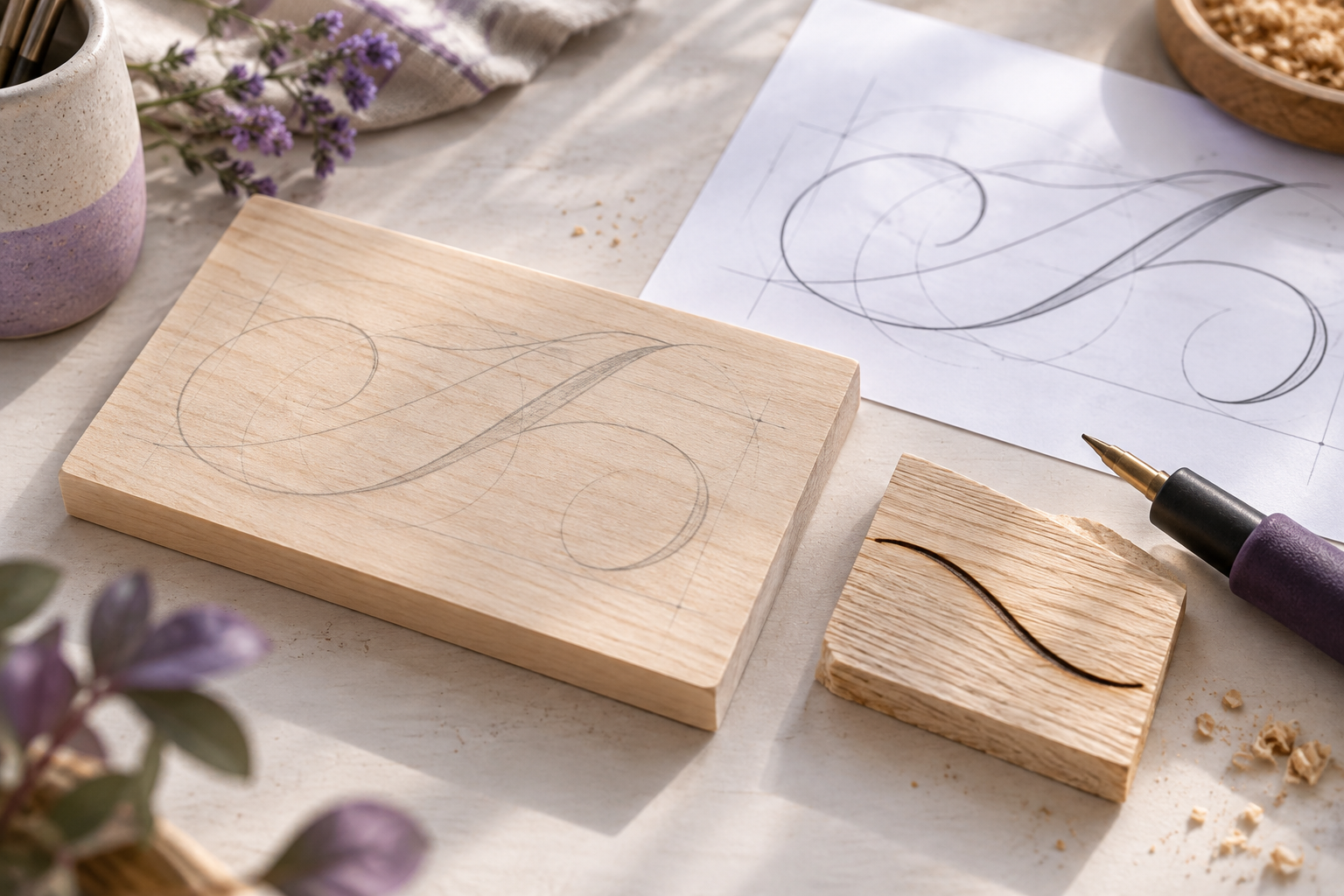
Надпись пирографом на дереве начинается не с выбора красивого шрифта, а с проверки того, какие его детали выдержат перенос и движение горячего пера. На древесине штрих может выглядеть иначе из-за направления волокон и неодинакового потемнения, поэтому готовый макет стоит упростить и испытать на обрезке того же материала.
Почему экранный макет не переносится на дерево один к одному
На экране буква выглядит как контур заданной толщины и ровного цвета. При выжигании её рисует не пиксель, а наконечник инструмента, который движется по поверхности и оставляет след с собственной шириной. На практике линия получается не абсолютно одинаковой на всём протяжении: на результат влияют скорость движения руки, контакт с поверхностью, древесный рисунок и выбранный наконечник. Поэтому тонкий штрих может стать слабым или прерывистым, а тесный просвет между элементами — закрыться.
Важно заранее решить, какую роль играет надпись. Короткое имя на небольшой подвеске можно сделать выразительным и крупным; фраза на табличке должна читаться с расстояния; длинная цитата требует прежде всего ровного ритма и достаточного межстрочного пространства. Один и тот же декоративный шрифт не одинаково подходит всем этим задачам. Сначала определяют формат изделия и расстояние чтения, затем выбирают характер букв.
На экране удобно масштабировать макет без потери качества, но физическая заготовка задаёт предел. Если надпись должна уместиться в узкой зоне между краем, креплением и естественным сучком, уменьшение целого макета одновременно сокращает внутренние просветы и расстояния между словами. Если свободного поля нет, лучше сократить текст или перестроить композицию, чем механически уменьшать кегль.
Как выбрать шрифт для пирографии
Для первой пробы выбирайте гарнитуру по силуэту слова, а не по названию стиля. Напишите реальную фразу в предполагаемом размере и посмотрите на неё целиком. У букв «о», «а», «е», «в» и «р» проверьте внутренние пространства; у «ш», «щ», «м» и «ж» — участки, где несколько штрихов сходятся близко. Если контуры уже на экране сливаются, выжигание не исправит проблему. Хороший кандидат читается в масштабе изделия без увеличения.
Рукописный шрифт может передать ручной характер вещи, но его петли и связки нужно оценивать отдельно. Соседние буквы не должны превращаться в сплошной тёмный участок после нанесения линии. Геометрический или нейтральный гротеск обычно проще для первой технической проверки: у него легче заметить тесные интервалы и сравнить ширину штрихов. Это не запрет на декоративные формы, а способ сначала проверить основу, а затем добавлять характер.
Не имитируйте толщину букв двойным проходом по контуру, если задача — получить обычную линейную надпись. Контурная буква требует замкнутой формы и отдельной проверки того, как будут выглядеть её внутренние и внешние линии. Для имитации плотного штриха иногда нужна обводка или заполненная форма, но на дереве такой участок может потребовать больше времени и дать неравномерный тон. Решение принимают на пробе, а не по экранному превью.
Откройте мелкие детали до переноса
В макете полезно увеличить те части, которые при уменьшении становятся особенно уязвимыми: внутренние просветы, короткие перекладины, острые соединения и тонкие окончания. Уменьшите текст до реального размера и распечатайте на обычной бумаге либо выведите рядом с контуром заготовки. Просмотрите его не только вблизи, но и с расстояния, с которого человек будет читать готовое изделие. Если слово узнаётся лишь при разглядывании листа, на готовом предмете оно тоже потребует лишнего усилия.
Вместо точного миниатюрного набора часто лучше слегка изменить рисунок: выбрать менее контрастное начертание, увеличить расстояния между буквами, убрать чрезмерно тонкие элементы или заменить сложную связку более ясной. Не растягивайте весь текст непропорционально только ради заполнения поля: буквы могут выглядеть деформированными. Настраивайте интервал и масштаб в пределах, при которых форма сохраняет привычные пропорции.
Отдельно проверьте сочетания русских букв, которые могут напоминать друг друга при малом размере, и знаки, важные для смысла: тире, точку, запятую, двоеточие. Если надпись содержит дату или инициалы, проверьте цифры и их порядок. Пирография превращает крошечную типографическую ошибку в постоянную отметку, поэтому тестовый набор должен повторять именно окончательный текст, а не условное слово из одинаковых букв.
Учитывайте волокна, сучки и направление композиции
Перед версткой разложите заготовку в том положении, в котором её будут рассматривать. Отметьте верх, низ, лицевую сторону, крепёж и участки, которые будут скрыты или закрыты рукой. Затем посмотрите на направление волокон и заметные природные особенности. Они не являются дефектом, который нужно маскировать любой ценой: задача в том, чтобы надпись оставалась различимой и не спорила с естественным рисунком.
Положите пробную распечатку на дерево и оцените, не проходят ли заметные линии волокон прямо через самые важные тонкие элементы текста. Если проходят, можно слегка сместить надпись, поменять её ориентацию или выбрать более крупный размер. Не пытайтесь автоматически размещать слова вдоль каждой линии рисунка: иногда это улучшает композицию, а иногда делает строку неестественной. Проверяйте общий баланс конкретной заготовки.